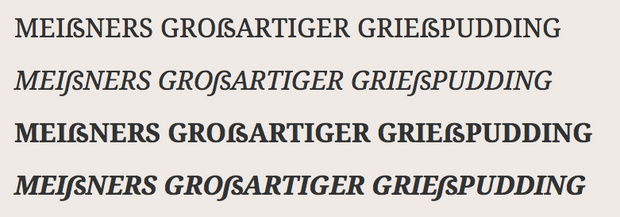
Großes Eszett im Forum
Das Versal-Eszett wird ja schon recht häufig hier im Forum eingesetzt. Wenn die zur Anzeige benutzte Schrift den Buchstaben allerdings nicht enthält, holt es sich der Browser entweder aus irgendeiner anderen Schrift oder man sieht sogar nur das berühmte NOTDEF-Zeichen. Nicht gerade optimal!
Für die hier im Forum als Webfont benutzte Droid Serif habe ich dies allerdings jetzt optimiert, indem ich für alle vier Schnitte ein entsprechendes Versal-Eszett entworfen und als Einzelzeichen-Webfont eingebettet habe.
MEIẞNERS GROẞARTIGER GRIEẞPUDDING Meißners großartiger Grießpuddung
MEIẞNERS GROẞARTIGER GRIEẞPUDDING Meißners großartiger Grießpudding
Alle diese Zeilen sollten mit einem korrekten und passenden Versal-Eszett zu sehen sein und dies funktioniert für gute 96 bis 98 Prozent aller Forennutzer – selbst wenn diese noch keine lokale Schrift mit einem Versal-Eszett installiert haben. Der Internet Explorer macht in diesem Zusammenhang wiedermal etwas Ärger, da zumindest die älteren Versionen kein Style-Linking beherrschen, aber ich habe versucht, dies durch spezifische IE-CSS-Angaben zu umgehen. Alle Browser, die mir zur Verfügung stehen, zeigen die Zeilen korrekt an.Falls jemand den Webfont Droid Serif sieht, nicht aber das passende Versal-Eszett (ẞ), bitte gern mit Angabe von Browser und OS bescheidsagen.
Bei mir in MacOS lasse ich einfach »ßß« automatisch in ẞ wandeln. Doppel-Eszett gibt's ja nicht und daher kann diese Ersetzung niemals unerwünschterweise auftreten.
MEIẞNERS GROẞARTIGER GRIEẞPUDDING Meißners großartiger Grießpudding
Hast Du Dich doch zu einem Versal-ß mit Unterlänge hinreißen lassen? Sehr chic. Obwohl ich Versalsatz in Cursiven ja eigentlich für Unsinn halte.
Oh, sehr schön, ein ſs-Eszet wie im Leipziger Duden, das sich wunderbar zum kleinen Eszet der Schrift fügt! Sehr gelungen!
Ja, das wäre natürlich auch möglich, aber ich möchte für diese Funktion nicht extra den Editor »hacken« und ihn dann nicht mehr direkt aktualisieren können.
Opera scheint einen seit Jahren bekannten Bug zu haben, dass fehlende Glyphen nicht in den weiteren Fonts des Font Stacks gesucht werden, sondern nach Gutdünken des Browsers aus dem System gefischt werden. Und dies entgegen der CSS2-/3-Spezifikationen. Nerv!
Oh, sehr schön, ein ſs-Eszet wie im Leipziger Duden, das sich wunderbar zum kleinen Eszet der Schrift fügt!
Zum kleinen Eszett mag’s passen, schön finde ich jedoch beide nicht. Das ist bitte nicht als Kritik an Deinen Fähigkeiten zu verstehen, Ralf, sondern liegt daran, daß ich die ſs-Form bekanntermaßen ablehne. In dem Fall wäre aber meines Erachtens alleine schon wegen der Bildschirmdarstellung und Größe die Dresdener Form wesentlich besser geeignet.
Darstellung in Firefox (oben) und Opera (unten, mit Eszett aus der DejaVu) im Vergleich:
33y051g.png
Die Droid scheint zudem kein oder kein ordentliches Hinting zu enthalten.
Getestet mit Win7, Directwrite-Rendering, Droid Serif an sich wird in allen Browsern geladen.
sieht bei mir korrekt aus in:
- FF9
- IE9
- Chrome15(?)
Und zeigt IE9 bei CSS-gesteuertem Versal-Satz jetzt tatsächlich standardmäßig ein Versal-Eszett?
Also zum Beispiel hier die Vorkommen von »FUSSBALL«? In einem anderen Strang hatte da ja mal jemand so angedeutet.
Und ich sehe bei der Gelegenheit gerade, dass Bigelow & Holmes doch tatsächlich in der TrueType-Version der Lucida Sans die damals noch unbelegte 1E9E-Stelle einfach mit einem Scedilla belegt haben. :bandit:Das ist natürlich nicht gerade im Sinne des Erfinders und macht die Abwärtskompatibilität beim Versal-Eszett-Einsatz nun nicht gerade einfacher.